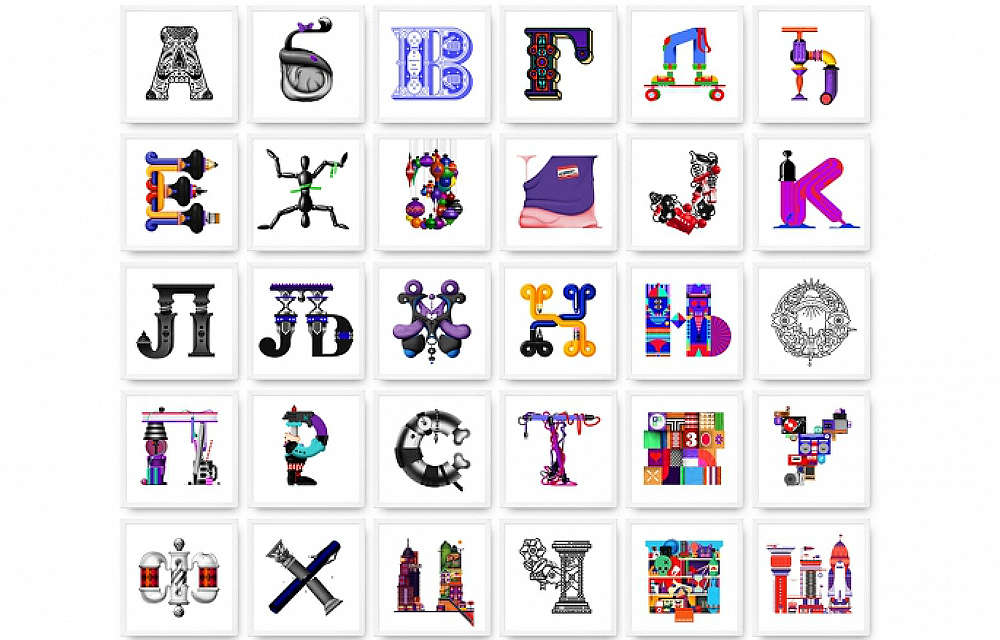
Aquí va una historia de letras.
uando se exploran los límites, cuando se lleva una disciplina a los márgenes inexplorados en los que confluye con otra realidad, ahí, en ese punto indefinido, se empiezan a obtener resultados interesantes. Bratislav Milenkovic nunca ha diferenciado muy bien entre tipografía e ilustración. «Básicamente, mi idea es intentar difuminar los límites al máximo», proclama. Así que su trabajo se mueve entre estas dos aguas, mecido entre la marea de las letras y la de los dibujos.
ratislav es serbio, lo cual puede explicar un montón de cosas. La convulsa historia de este pequeño país balcánico ha dado como resultado un collage de culturas que se cuela en la vida de sus habitantes desde la escuela. Allí se estudia serbio, el idioma oficial y mayoritario del país, que admite en su escritura tanto el alfabeto latino como el cirílico. Mientras la mayoría de estudiantes aprenden de pequeños las grafías de 26 letras, los serbios aprenden a trazar 66. Esta sopa de letras gráfica fue el caldo de cultivo perfecto para un artista como Bratislav. Desde que empezara a dar sus primeros pasos en el mundo de la ilustración, la tipografía se fue colando en sus diseños.
veces no está presente. Cuando tiene un encargo para alguna publicación -medios como The New York Times, Wired o Financial Times solicitan asiduamente sus servicios-, deja a un lado las letras y se centra en la ilustración. Pero en la mayoría de sus proyectos personales Bratislav experimenta con las reglas de una y otra disciplina. A veces lo hace de forma sutil, integrando un texto escondido entre sus dibujos, un mensaje camuflado que se integra a la perfección en su diseño. «Disfruto con la posibilidad de hacer que un texto pueda decir mucho más que su estricto significado», declara. Otras veces lo hace abiertamente, convirtiendo la tipografía en la auténtica protagonista, diseñando letras y dotándolas de una personalidad propia. Hasta hace poco lo había hecho de forma desordenada, salpicando sus trabajos con obras puntuales, mezclando como buen serbio los alfabetos latino y cirílico.
ero hace un año tuvo la oportunidad de convertir estos trabajos en una serie, de terminar las letras que le faltaban y completar el abecedario cirílico para la exposición Letters. «Considero de hecho que este alfabeto tiene caracteres ricos e interesantes y no se usa mucho en el campo de la tipografía ilustrada», reflexiona Bratislav.«El caso es que ha probado ser un campo de juegos muy inspirador».
l alfabeto de Bratislav tiene muchas influencias. 30 para ser exactos, una por cada letra. Más allá de tirar de folclore balcánico, el autor no duda en reflejar ecos de la tradición mexicana o de los elementos típicos de la ilustración. «Empecé a buscar temas que encajaran bien en la forma de cada letra», aclara al respecto. Y empezó a explorar los límites de una y otra disciplina. Y a obtener resultados interesantes. Juzgad vosotros mismos.
Tipografía cirílica ilustrada